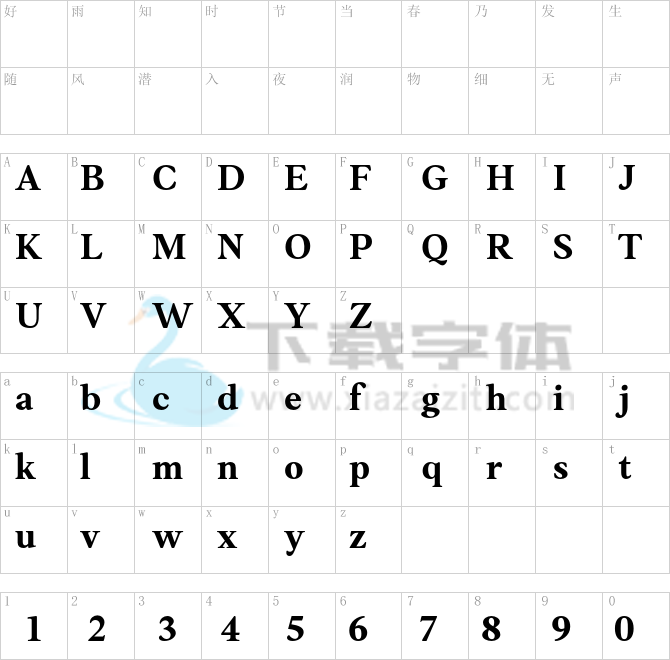
Anko Personal Use.otf字体下载,这款字体结构工整、笔画清晰,兼顾美观与易读性,适用于标题、正文、海报、包装、LOGO 等多种场景。字形优雅稳定,风格百搭耐看,适配日常排版与创意设计,让文字呈现更舒适、更具质感。Anko Personal Use.otf字体下载一笔一画,皆是细节,以均衡的比例、流畅的线条打造舒适视觉体验,字形端正大气,风格简约现代。无论是商业设计、品牌宣传还是日常排版,都能轻松驾驭,让文字更有格调与力量。Anko Personal Use.otf字体下载字体下载。